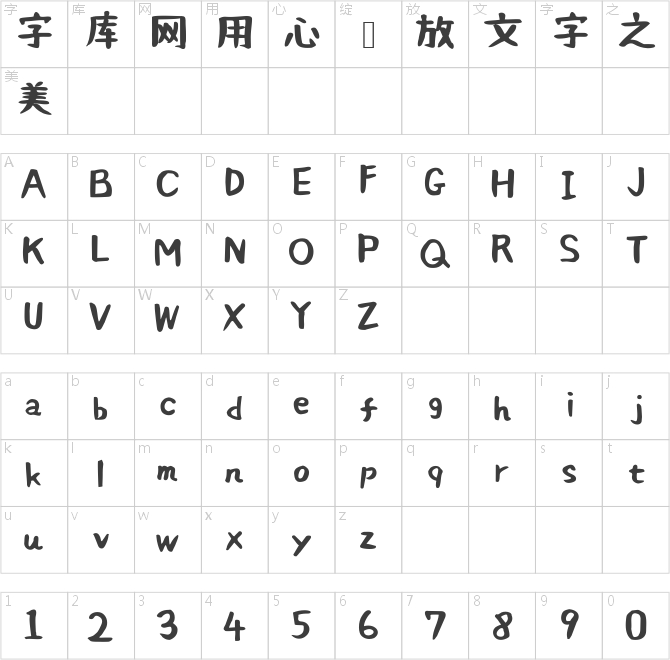
字體名稱: 何某手寫體
何某手寫體是Max基于日本的おつとめフォント字體增補修改而成的一款隨心所欲的手寫體。與原作者的主要差異是調整部件寫法、新增中文字、增加為5個字重、增加一些符號。經過Max的增補,何某手寫體對簡體的字體支持也挺不錯的。
對現代人來說,毛筆字體不是可讀性好的字體。但是手寫文字和勘亭流等優秀的文字經常被用于促銷用的傳單和海報等。因此,何某手寫體是根據毛筆文字的使用實際情況,重視“可視性高”為目標而制作的字體,大家不妨試一下哦。